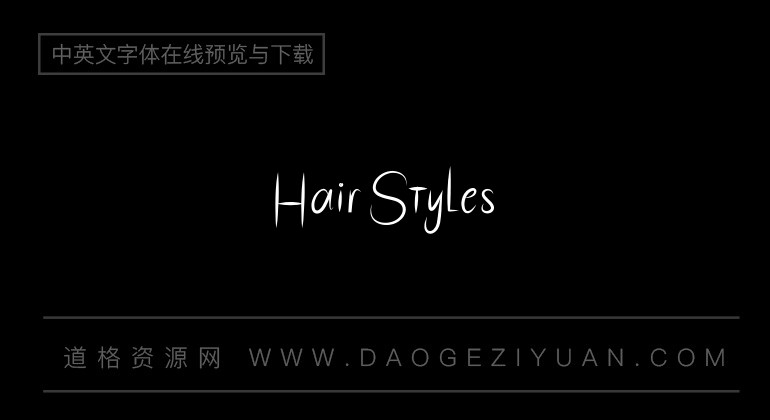
? HairStyles 字体是一款具有流行感的字体,它融合了现代复古风格,特别适合用于商业、时尚等领域的文字排版。它的字体线条粗细柔和,字形精致,具有良好的可读性,能够为文字排版带来更多的艺术感和视觉冲击力。内容介绍
HairStyles是一款非常不错的手写艺术字体,具有很好的视觉感,适合于文化类的宣传设计、商业类品牌的广告和产品包装设计以及个性化文字排版等较多场景。